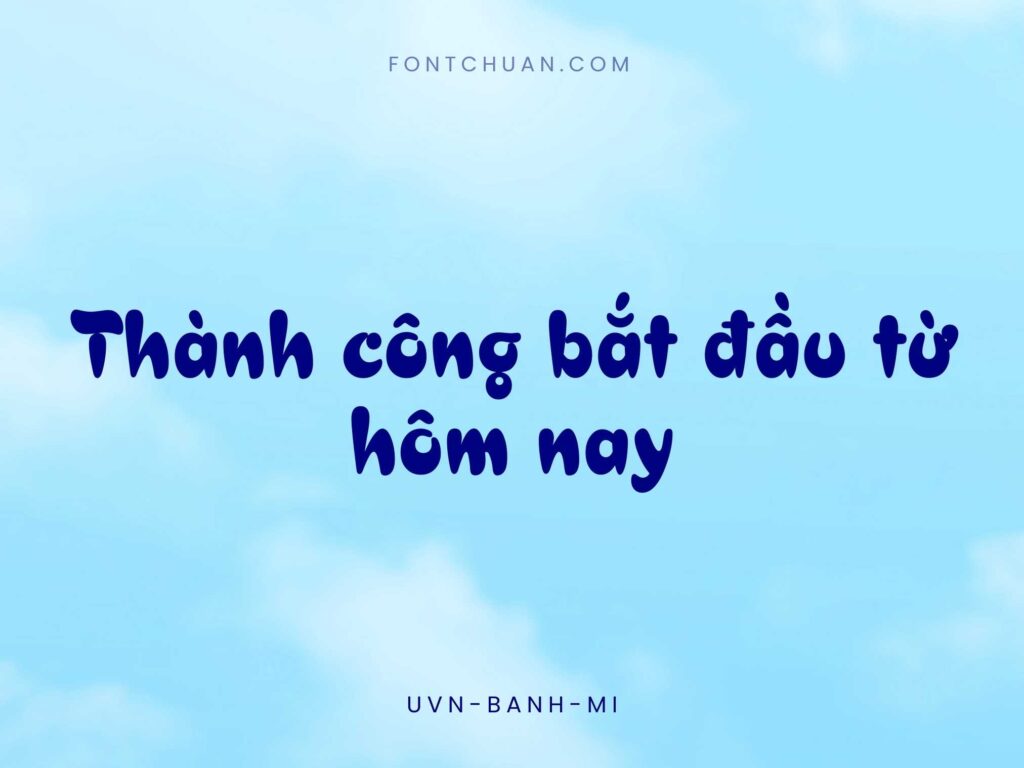
Font UVN Banh My Việt Hóa
UVN Bánh Mì là một phông chữ sans-serif được thiết kế bởi Tom Trương vào năm 2001. Phông chữ này mang lại cảm giác vui nhộn và thân thiện cho các thiết kế, với các đường nét mềm mại và hình dạng tròn trịa, tạo nên sự tươi vui và sáng tạo. UVN Bánh Mì hỗ trợ đầy đủ các ký tự tiếng Việt, giúp người dùng dễ dàng sử dụng trong nhiều loại dự án khác nhau.
Với thiết kế độc đáo và nghệ thuật, UVN Bánh Mì phù hợp cho các ứng dụng như thiệp mời, tiêu đề sách, thiết kế logo và các ấn phẩm nghệ thuật. Trong lĩnh vực sự kiện, phông chữ này có thể được sử dụng trong các dịp như lễ hội, sinh nhật và các sự kiện văn hóa. Ngoài ra, UVN Bánh Mì cũng thích hợp cho các ngành nghề như thiết kế đồ họa, nghệ thuật trang trí và xuất bản.